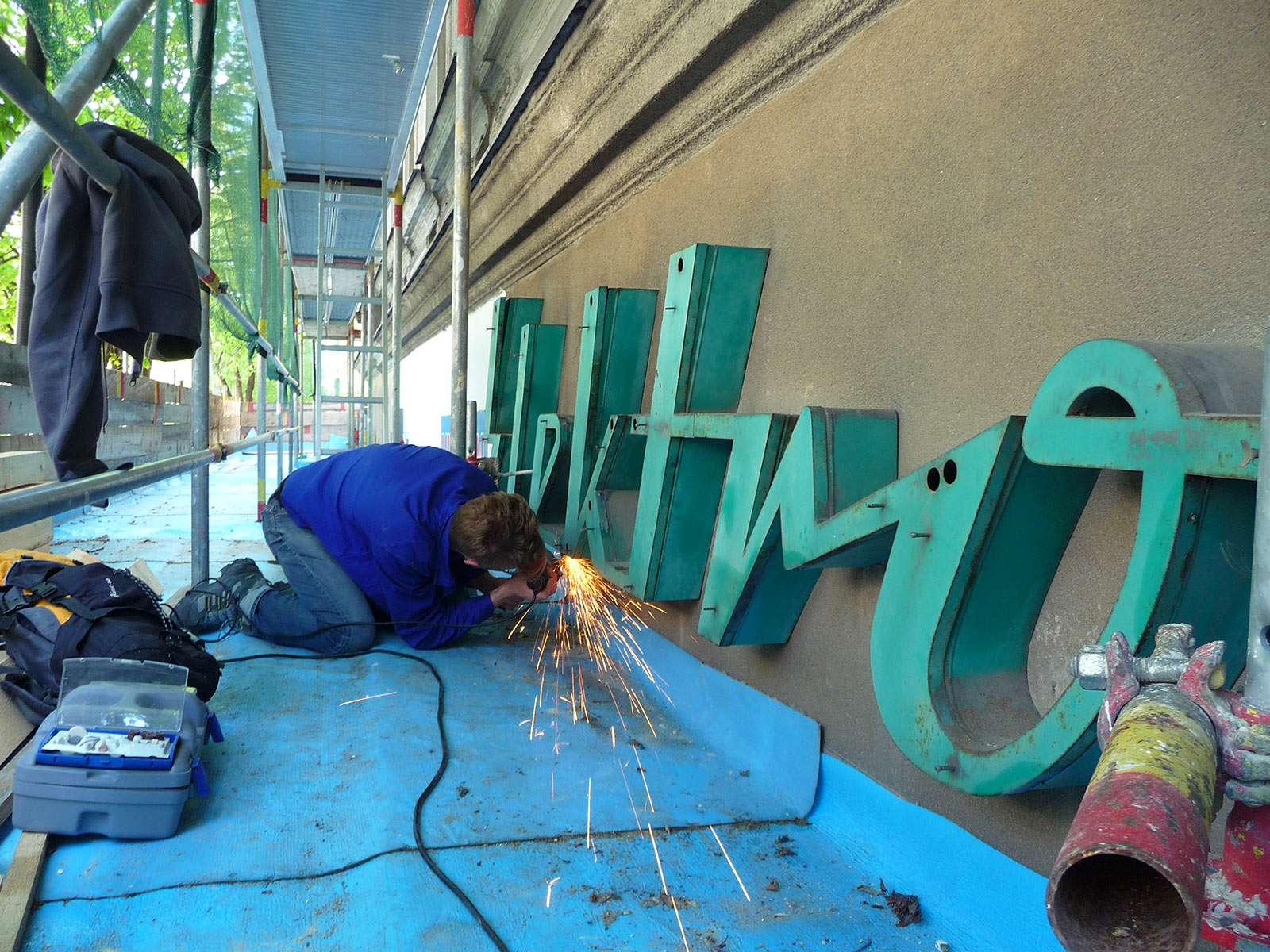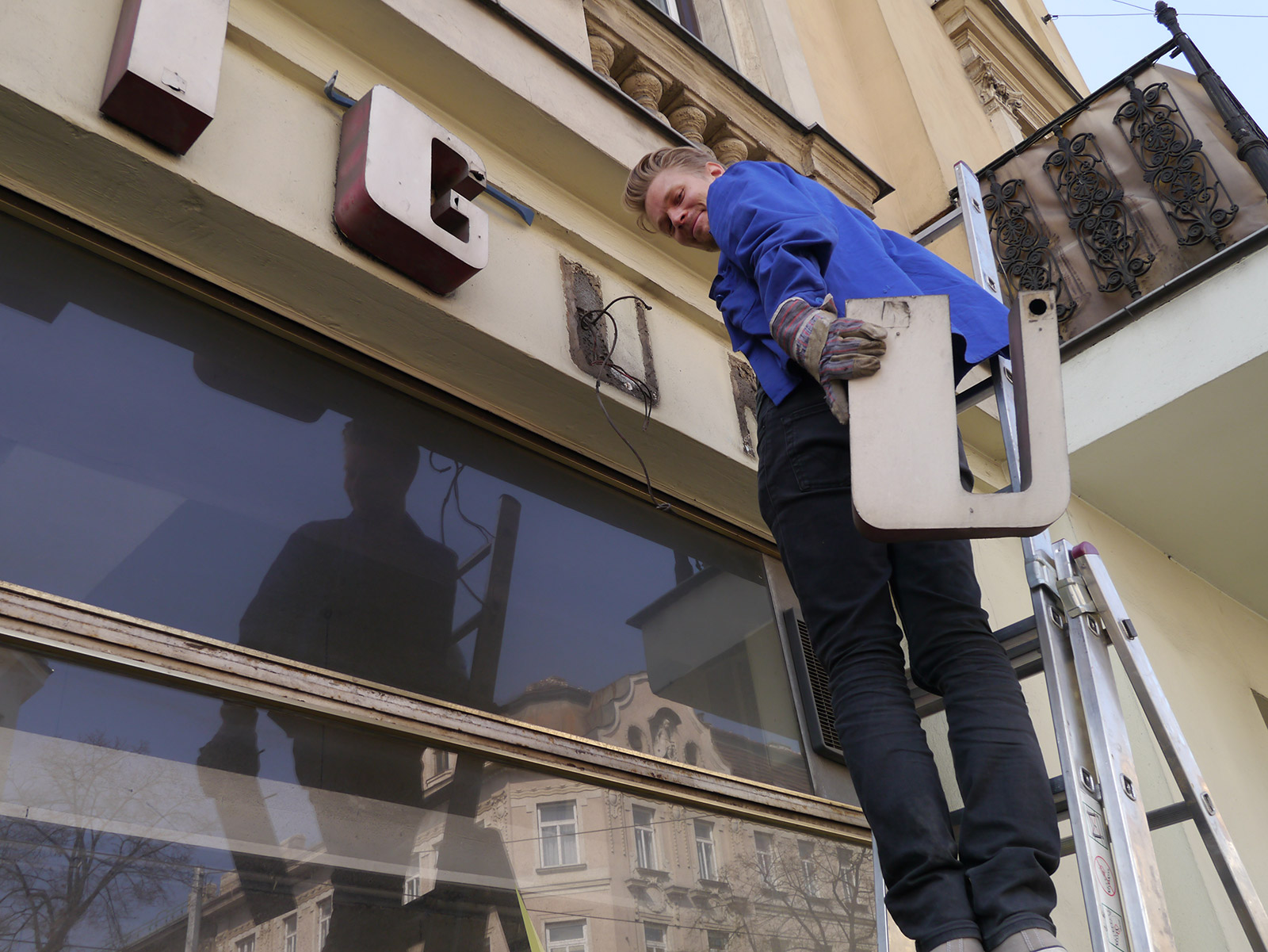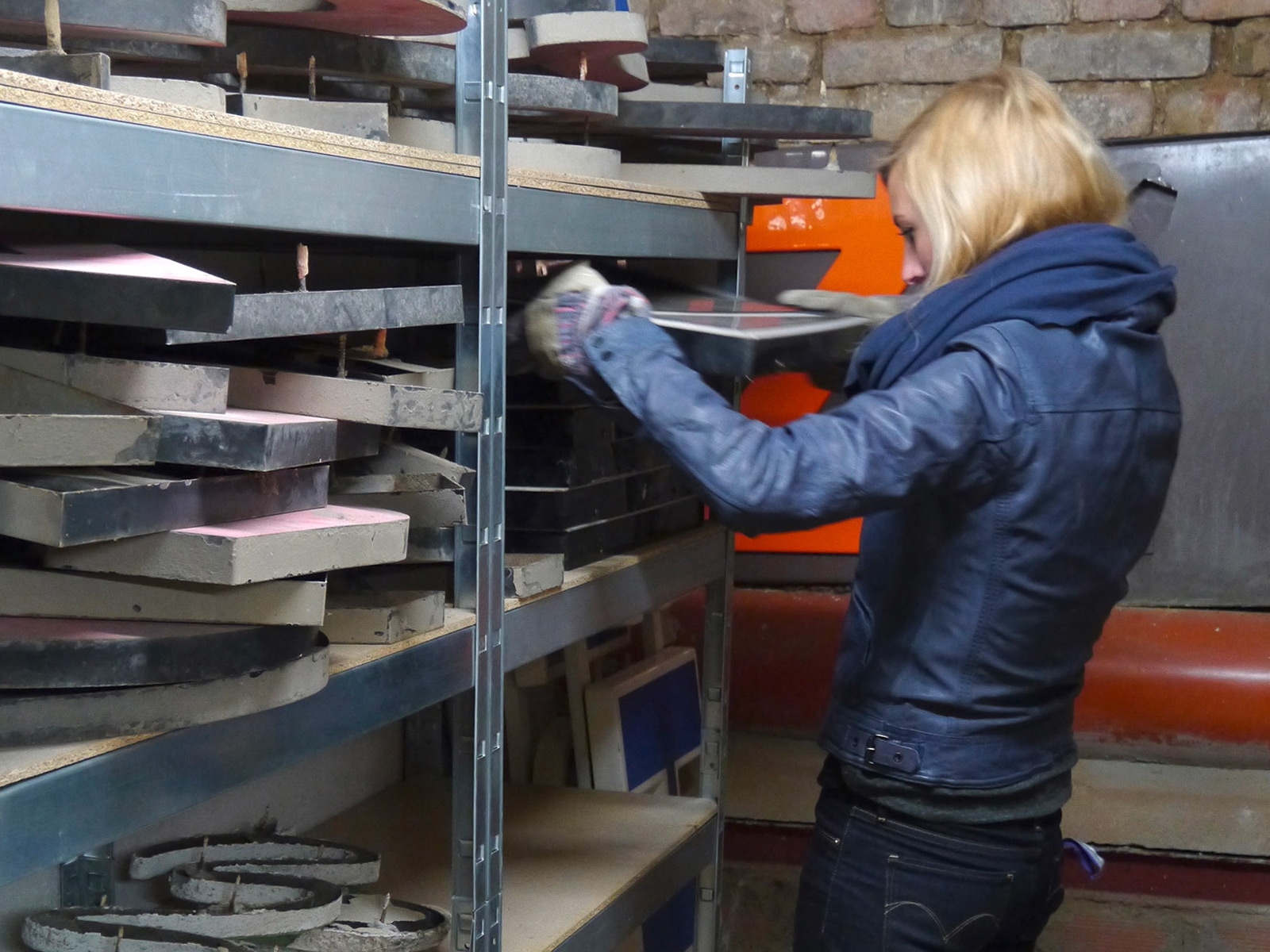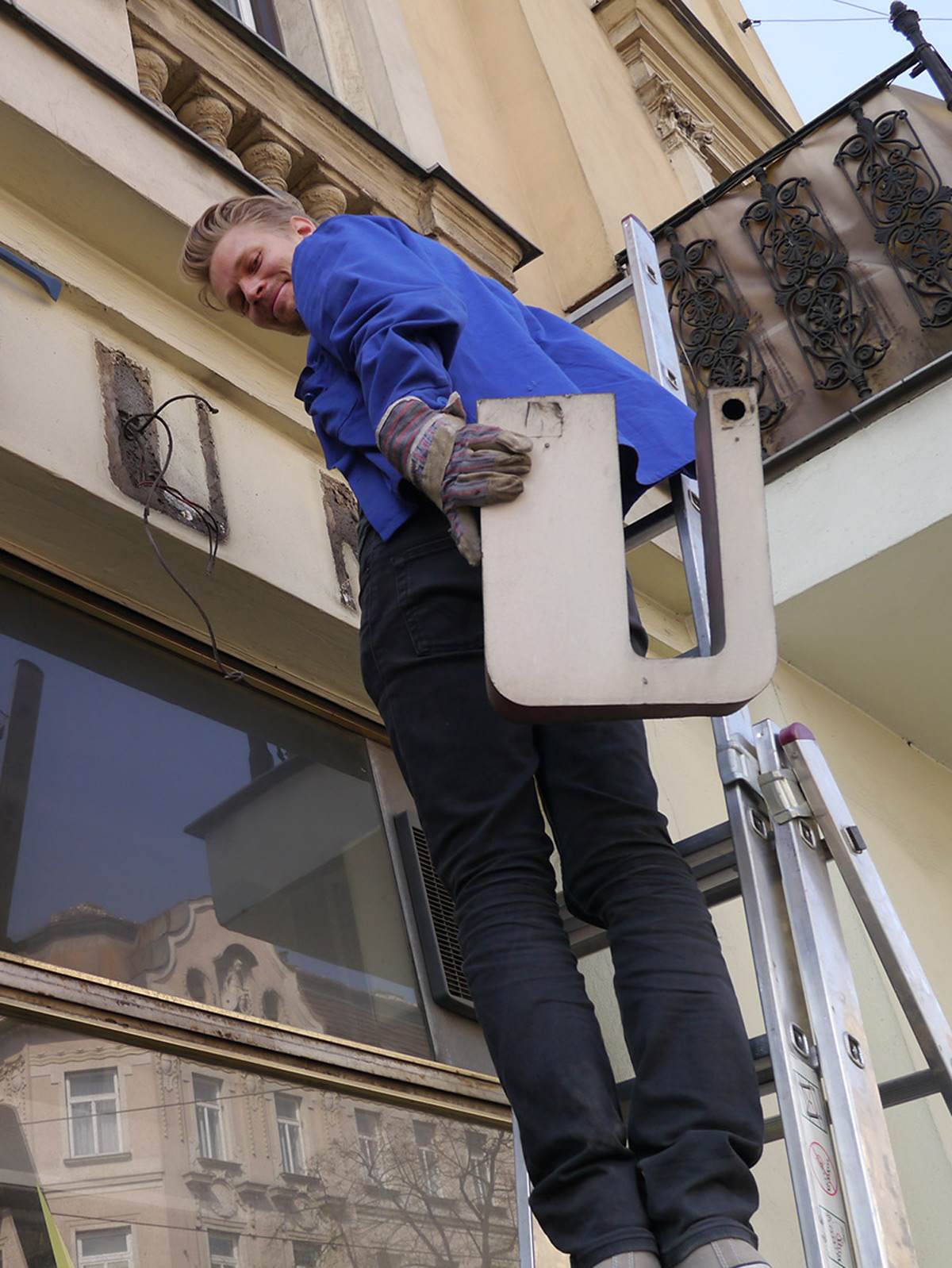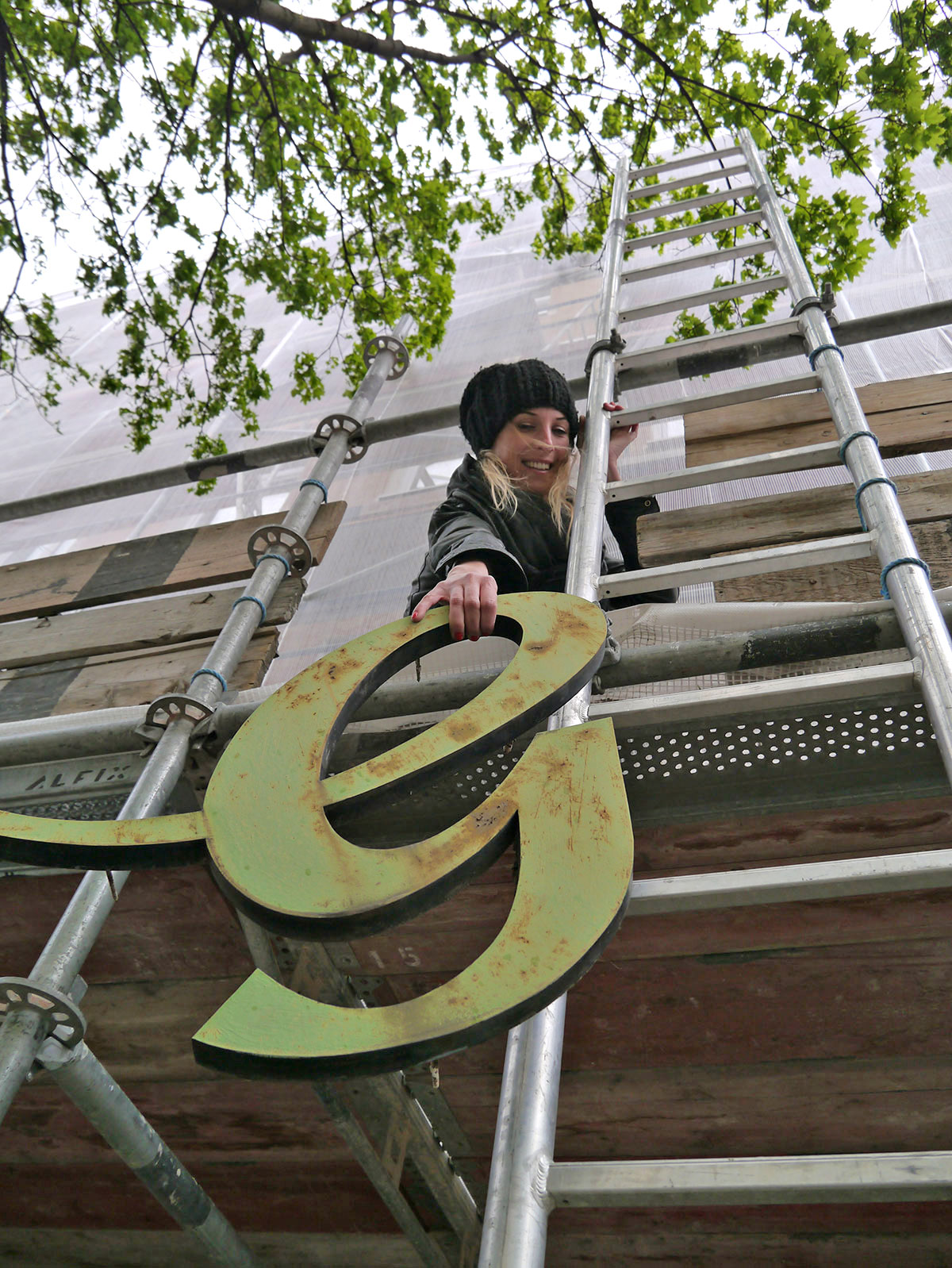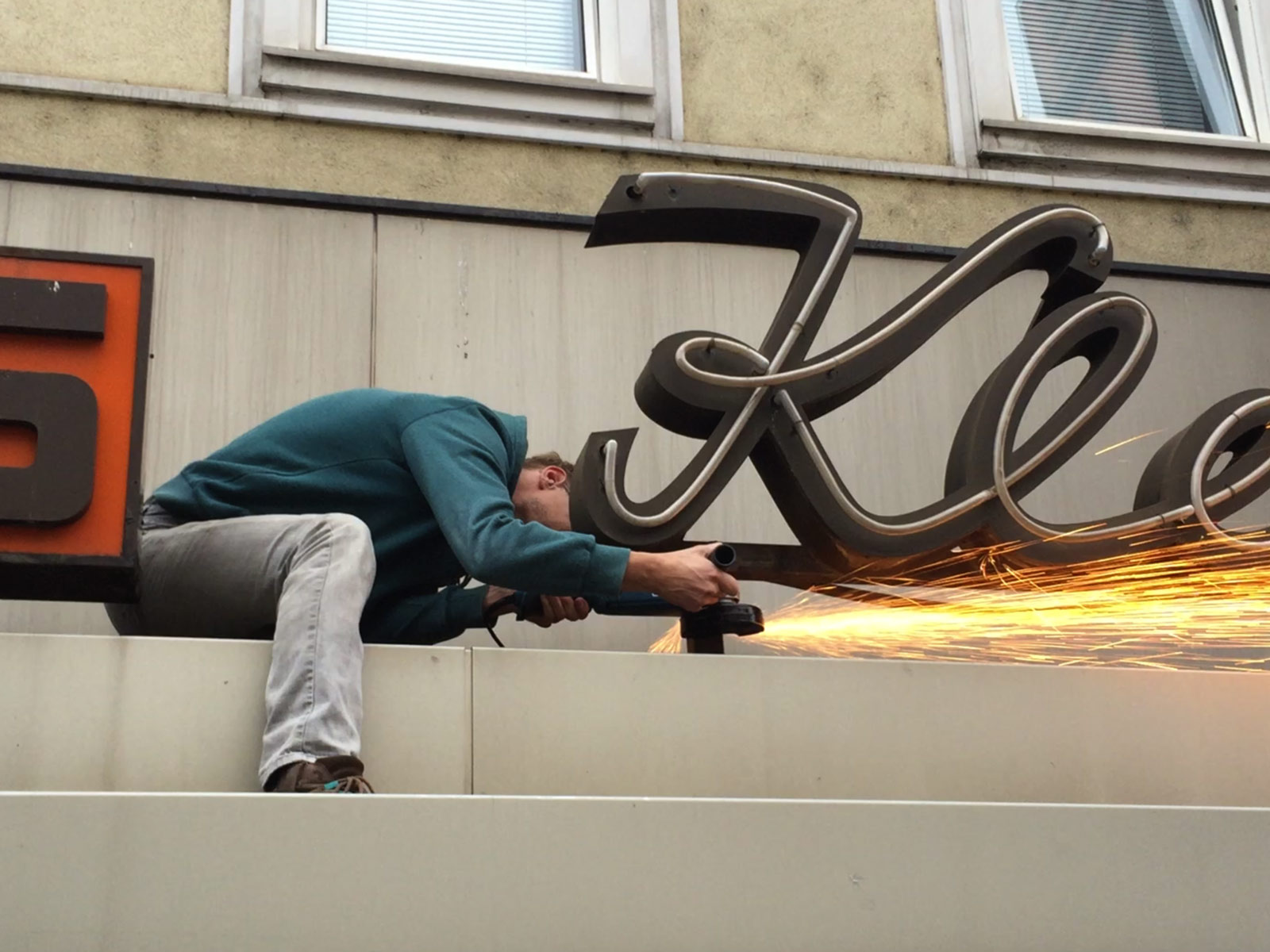
Stadtschrift
Verein zur Sammlung, Bewahrung und Dokumentation historischer Fassadenbeschriftungen
Der Verein Stadtschrift wurde im März 2012 als Initiative gegründet, obsolet gewordene historische Wiener Geschäftsbeschriftungen zu dokumentieren und vor der Verschrottung zu bewahren. Unser Anliegen ist, das Bewusstsein für die „Handschrift“ unserer Stadt zu fördern, indem wir obsolet gewordene Schriftzüge mit identitätsstiftender Bedeutung sammeln und für die Öffentlichkeit wieder zugänglich machen.
In Wien haben vergleichsweise viele Schriftzüge aus den 50er- und 60er-Jahren überlebt. In den vergangenen Jahren ist der Strukturwandel in den Geschäftsstraßen jedoch rapide fortgeschritten, Kleinbetriebe werden zunehmend von Handelsketten verdrängt. Mit den alteingesessenen Geschäften verschwinden auch ihre handwerklich wertvollen Beschriftungen, was befürchten lässt, dass die typografische DNA Wiens bald nicht mehr existieren wird. Denn alte Schriftbilder bestimmen die Identität und die Unverwechselbarkeit einer Stadt, wir sehen sie als Kulturerbe, das erhalten gehört!